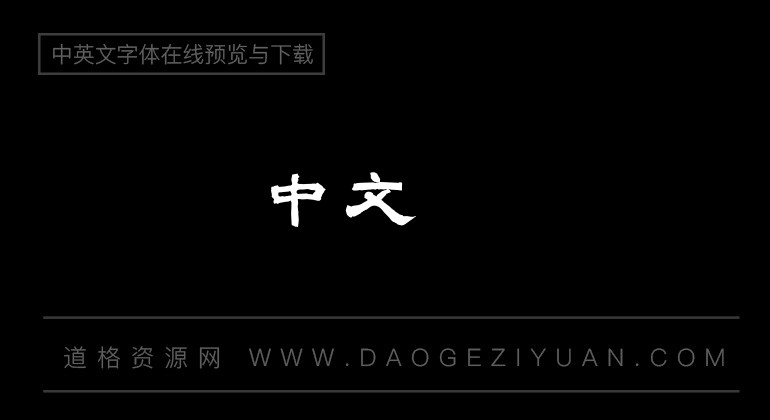
迷你繁唐隶
迷你繁唐隶字体是一种简洁、精致的中文字体,由深圳市大字体科技有限公司开发,源自中国传统的繁体字,经过精心设计,拥有清新、精致的外观,简洁的线条,清晰的结构,极具表现力。迷你繁唐隶字体可以用于多种印刷品、网页设计、平面设计等多种应用场景,能够为作品带来更加清新、精致的视觉效果。
迷你繁唐隶是一款非常不错的手写艺术字体,具有很好的视觉感,适合于文化类的宣传设计、商业类品牌的广告和产品包装设计以及个性化文字排版等较多场景。